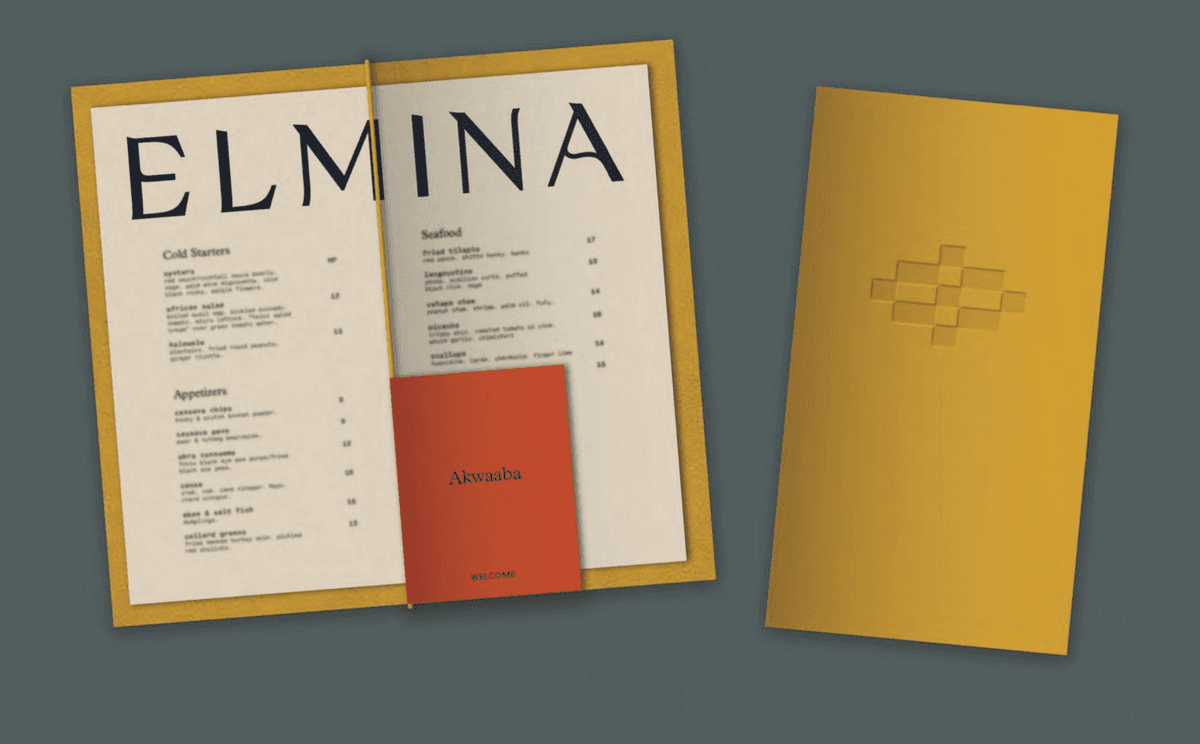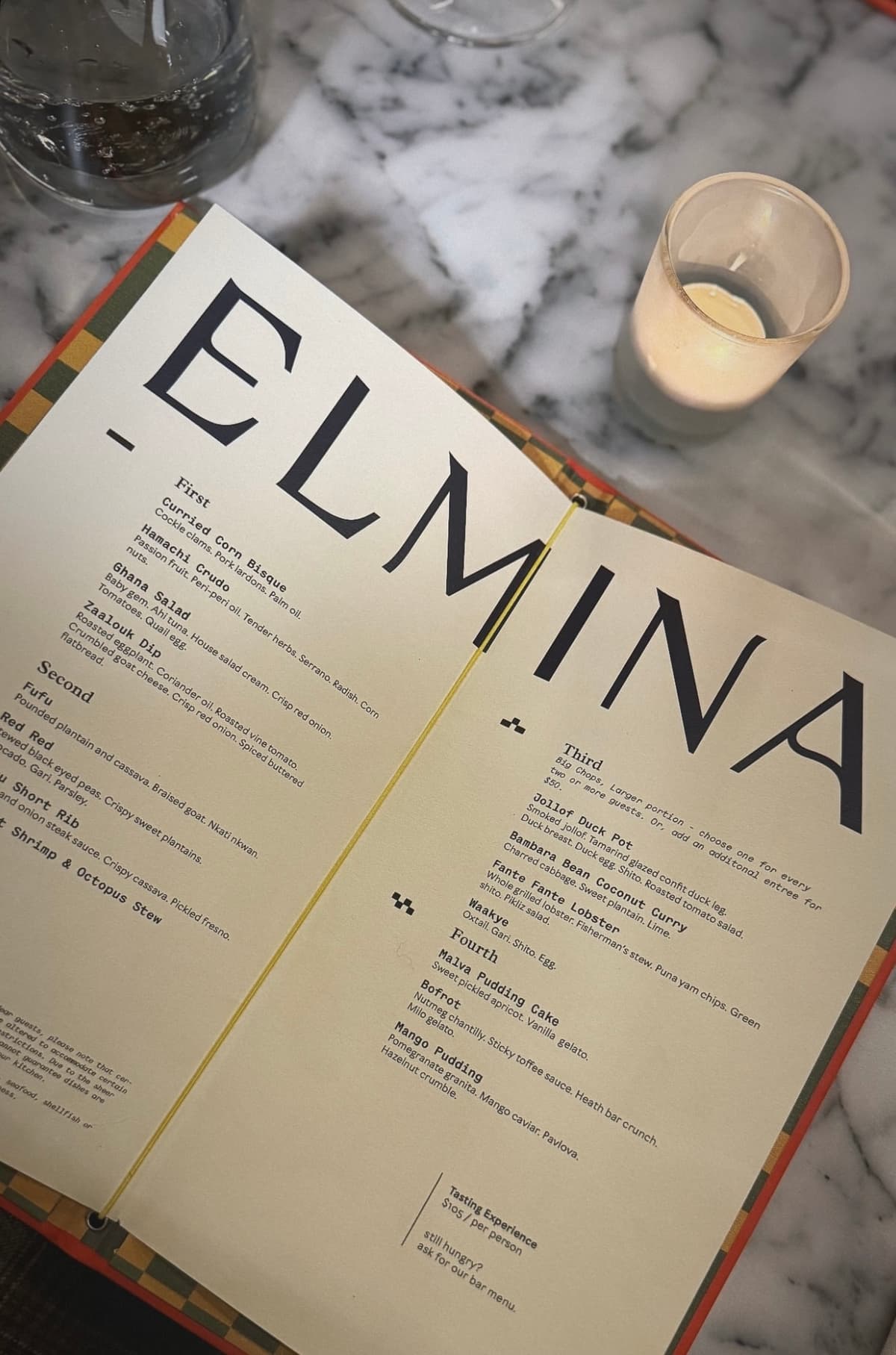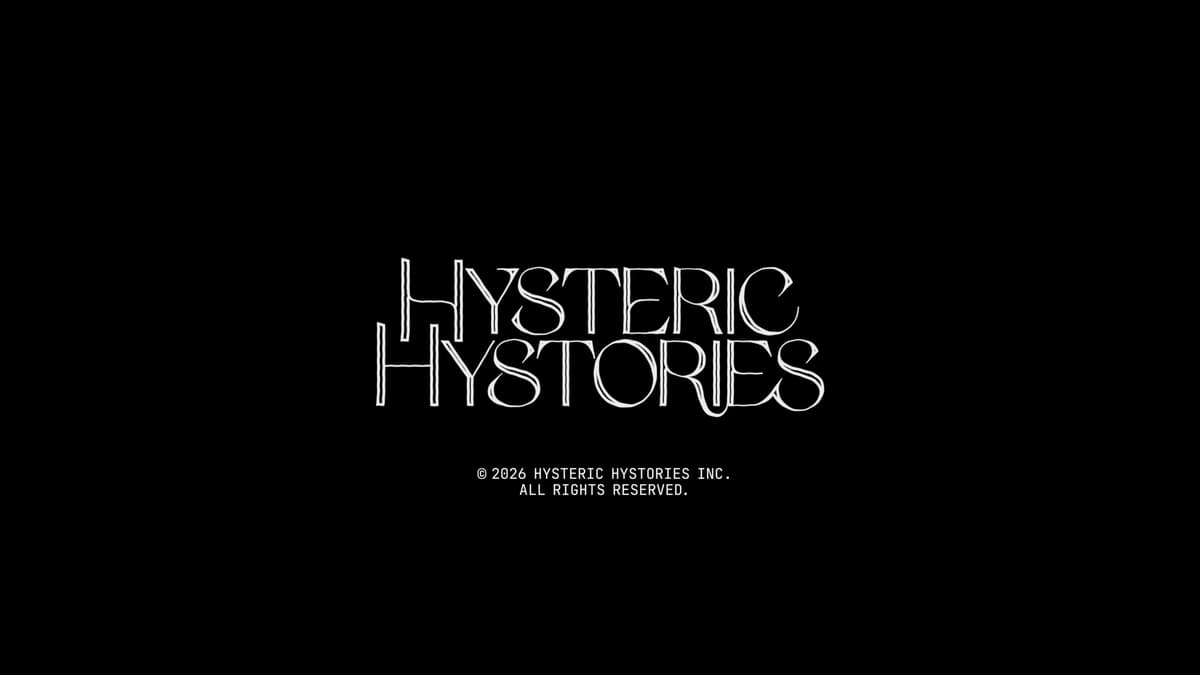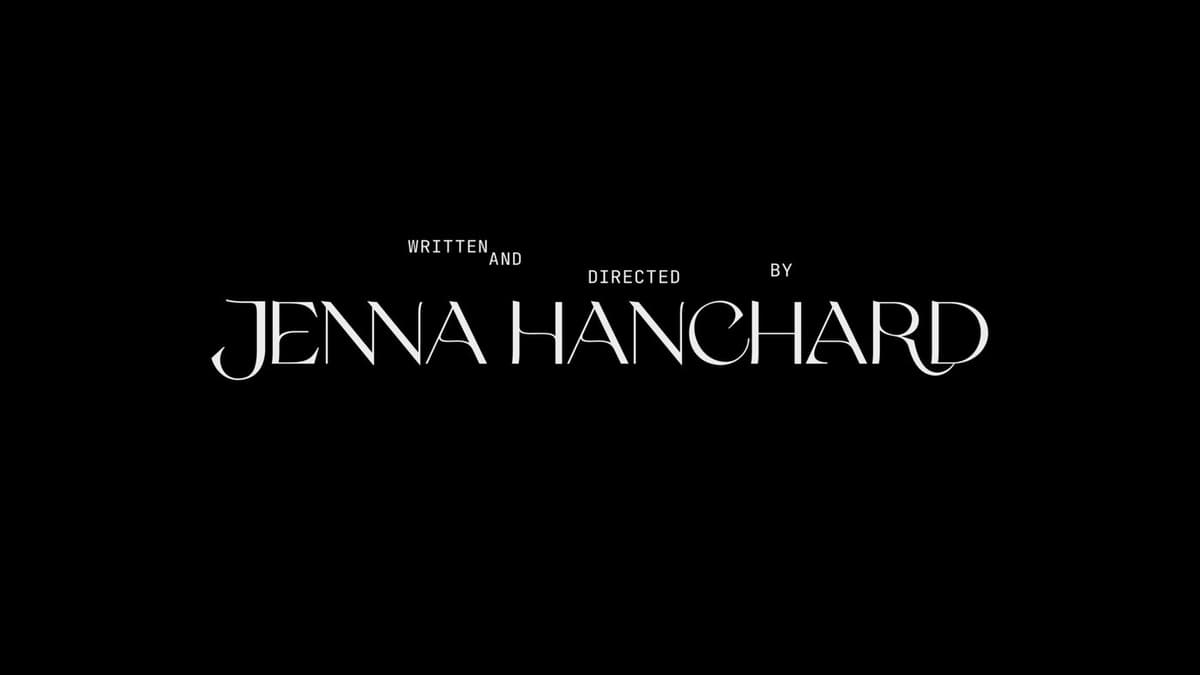
OS Korhogo Tisserand
Magical design for beauty alchemists.
Dessinée avec la dévotion du maître tisserand.
Chaque pièce tissée est le fruit d'un savoir-faire unique, où les motifs portent des noms évocateurs tels que "dents de panthère", "cauris" ou "peau d'ananas", reflétant les usages spécifiques des vêtements lors des événements importants comme les fêtes d'initiation ou les mariages.
OS Korhogo Tisserand is the formal instrument of the weaver's state, the creative mode that finds beauty in devotion, complexity in repetition, and meaning in what emerges when elements are threaded together with care. Korhogo's weavers have encoded their worldview into cloth for centuries. This typeface channels their wisdom.